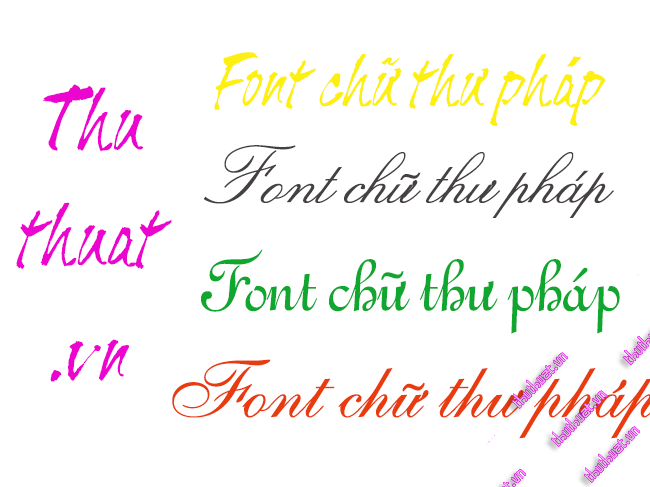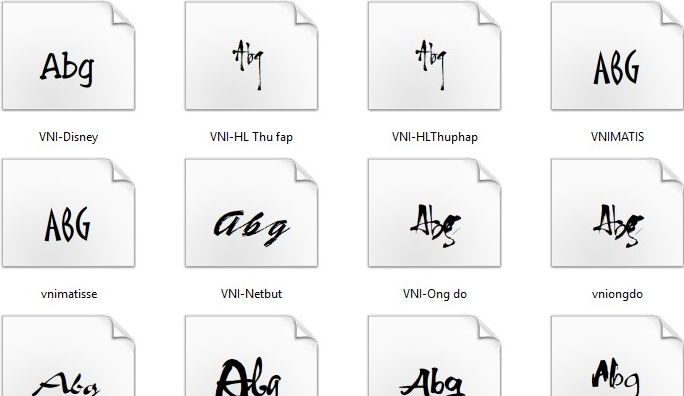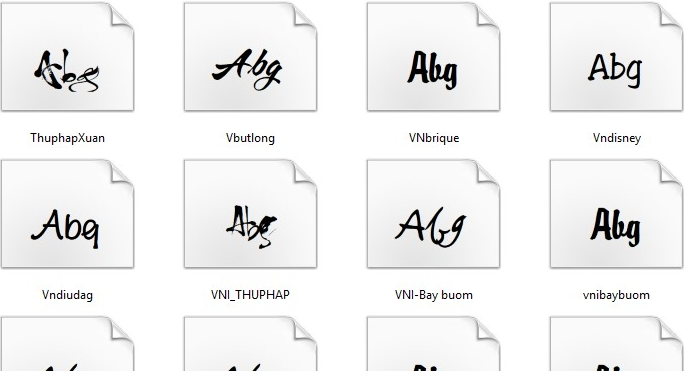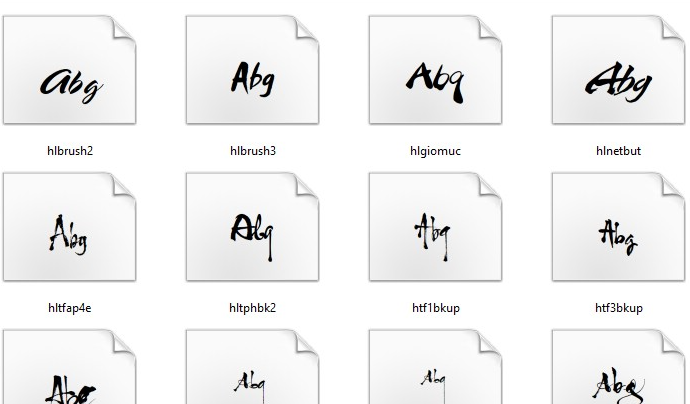
Bạn muốn gõ văn bản rông bay phượng múa, muốn tạo những đường nét uốn lượn. Thế nhưng font chữ mặc định trong Windows lại không thể làm được điều này mà chúng ta phải sử dụng font chữ thư pháp. Giờ đây bạn không cần hoa tay hay tài năng mà chỉ cần gõ chữ thư pháp ở máy tính và in ra là đã có những chữ thư pháp đẹp tuyệt vời. Dưới đây là bộ font thư pháp hay còn gọi là font ông đồ mà tip.com.vn  tổng hợp được. Đây là bộ font với những nét chữ phá cách uống lượn vô cùng độc đáo.  Với bộ font thư pháp Việt hóa này bạn hoàn toàn có thể gõ sáng tạo ra những chữ thư pháp tuyệt đẹp.  Cùng tải về và trải nghiệm nhé
Demo một số hình ảnh về các font chữ thư pháp cực đẹp cho thiết kế 2020